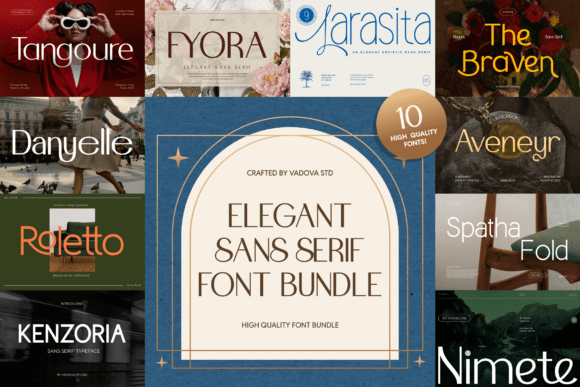
Elegant Sans Serif Bundle
Если вы ищете высококачественные ресурсы, такие как Elegant Sans Serif Bundle, этот премиум-пакет — фантастический выбор для ваших творческих проектов.
Создаете ли вы продукты POD (печать по требованию), свадебные приглашения или графику для социальных сетей, Elegant Sans Serif Bundle станет идеальным выбором.